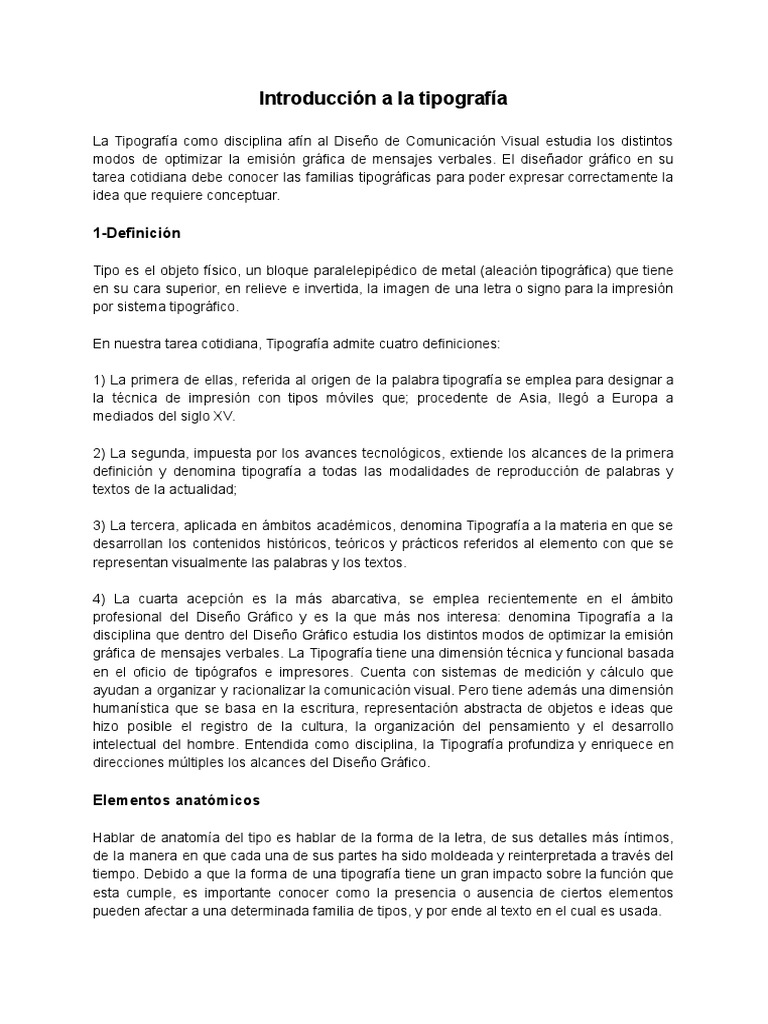
Introducción a la tipografía
La Tipografía como disciplina afín al Diseño de Comunicación Visual estudia los distintos
modos de optimizar la emisión gráfica de mensajes verbales. El diseñador gráfico en su
tarea cotidiana debe conocer las familias tipográficas para poder expresar correctamente la
idea que requiere conceptuar.
1-Definición
Tipo es el objeto físico, un bloque paralelepipédico de metal (aleación tipográfica) que tiene
en su cara superior, en relieve e invertida, la imagen de una letra o signo para la impresión
por sistema tipográfico.
En nuestra tarea cotidiana, Tipografía admite cuatro definiciones:
1) La primera de ellas, referida al origen de la palabra tipografía se emplea para designar a
la técnica de impresión con tipos móviles que; procedente de Asia, llegó a Europa a
mediados del siglo XV.
2) La segunda, impuesta por los avances tecnológicos, extiende los alcances de la primera
definición y denomina tipografía a todas las modalidades de reproducción de palabras y
textos de la actualidad;
3) La tercera, aplicada en ámbitos académicos, denomina Tipografía a la materia en que se
desarrollan los contenidos históricos, teóricos y prácticos referidos al elemento con que se
representan visualmente las palabras y los textos.
4) La cuarta acepción es la más abarcativa, se emplea recientemente en el ámbito
profesional del Diseño Gráfico y es la que más nos interesa: denomina Tipografía a la
disciplina que dentro del Diseño Gráfico estudia los distintos modos de optimizar la emisión
gráfica de mensajes verbales. La Tipografía tiene una dimensión técnica y funcional basada
en el oficio de tipógrafos e impresores. Cuenta con sistemas de medición y cálculo que
ayudan a organizar y racionalizar la comunicación visual. Pero tiene además una dimensión
humanística que se basa en la escritura, representación abstracta de objetos e ideas que
hizo posible el registro de la cultura, la organización del pensamiento y el desarrollo
intelectual del hombre. Entendida como disciplina, la Tipografía profundiza y enriquece en
direcciones múltiples los alcances del Diseño Gráfico.
Elementos anatómicos
Hablar de anatomía del tipo es hablar de la forma de la letra, de sus detalles más íntimos,
de la manera en que cada una de sus partes ha sido moldeada y reinterpretada a través del
tiempo. Debido a que la forma de una tipografía tiene un gran impacto sobre la función que
esta cumple, es importante conocer como la presencia o ausencia de ciertos elementos
pueden afectar a una determinada familia de tipos, y por ende al texto en el cual es usada.
Desde sus orígenes los caracteres han sufrido una constante transformación, de lo antiguo
a lo moderno, de lo sobrio a lo exagerado, de lo orgánico a lo sintético. Durante este
proceso han recibido infinidad de aportaciones, muchas veces dependiendo del contexto
histórico, político, económico y social del que formaban parte. Es gracias a estas
características que podemos clasificar las tipografías, aun cuando surgen ciertos conflictos
para llevar a cabo dicha tarea
Clasificación
Familias tipográficas
Una familia tipográfica es un grupo de tipografías unidas por características similares. Los
miembros de una familia (los tipos) se parecen entre sí, pero también tienen rasgos propios.
Las tipografías de cada familia tienen distintos grosores y anchos. Algunas familias las
forman muchos miembros, otras sólo de unos pocos.
Fuentes tipográficas
La palabra fuente se utiliza actualmente para describir todos los elementos anteriores más
las cursivas, finas y negras de la misma familia de tipos. Una tipografía está compuesta por
los conjuntos de caracteres representados por todos los tamaños y grosores de una
determinada clase de letra.
Resumen
El tipo básicamente es un caracter de impresión, una tipografía está compuesta por los
conjuntos de caracteres representados por todos los tamaños y grosores de una
determinada clase de letra los cuales son indispensables en el diseño gráfico. Los tipos se
pueden clasificar en fuentes, familias y series, para lograr estas clasificaciones nos vamos a
aprovechar de sus rasgos característicos y estilos.
Conclusión
La clasificación de los tipos y sus características nos va ayudar a identificarlos y poder
expresar la idea o mensaje que queramos o necesitemos.
2- Estructura
El vocabulario usado para la descripción de las diferentes partes que estructuran una letra,
se compone de una serie de términos acuñados desde hace mucho tiempo y que se
asemejan a los usados para describir las partes de nuestro cuerpo. Así las letras tienen
brazos, piernas, ojos, y otras partes como cola.
De cualquier forma, por problemas de traducción, la descripción de las partes de una letra
no coinciden de forma unánime en los libros sobre tipografía y diseño. En todo caso los
términos que aquí se reflejan constituyen un buen bagaje para comprender y conocer las
distintas partes de una letra.
Clasificación tipográfica
En la actualidad el universo de las tipografías resulta extremadamente amplio, más teniendo
en cuenta que gracias al desarrollo de las herramientas de informática y computación el
número se acrecienta en forma constante y a un ritmo sorprendente. Resulta prácticamente
imposible conocer por sus nombres la totalidad de las fuentes tipográficas, por lo que
intentar realizar una clasificación tipográfica comienza a tener sentido.
Una clasificación puede ser abordada desde ópticas diferentes:
● Una forma muy amplia de dividir el inmenso universo tipográfico puede ser teniendo
en cuenta la función o el empleo que se haga de la tipografía. Los dos grandes
grupos que se pueden reconocer con cierta facilidad en este sentido son: por un
lado, los de las tipografías que sirven para textos de largo alcance, es decir
tipografías que deben leerse con facilidad, y en cuanto a su morfología, no deben
llamar la atención. Y por otro lado estarían las tipografías de rótulo. Estas son
tipografías que deben llamar la atención por sobre todo, y por supuesto deben poder
leerse, aunque no son recomendables para textos largos.
● Otra clasificación elemental está basada en características relacionadas con la
anatomía de la letra, y si bien toma como referente la clasificación realizada por
Maximilian Vox en 1954, apunta a lograr una simplificación respecto a los estilos
transicionales. La clasificación aquí propuesta reconoce cuatro amplios grupos o
conjuntos básicos:
○ Tipografías Serif (Con Serif o Roman),
○ Tipografías Lineales (Sin Serif o Paloseco),
○ Tipografías Cursivas (o Script) y
○ Tipografías Decorativas (o Graphic)
Cada conjunto está subdividido en estilos, de los cuales a continuación daré algunas
características básicas y ejemplos de fuentes digitalizadas.
Sin desmedro de la clasificación propuesta, existen en la actualidad familias tipográficas
seriales o superfamilias que superan todas las barreras de los grupos clasificatorios, como
por ejemplo la tipografía Rotis, diseñada por Olt Aicher, que presenta un programa
tipográfico de cuatro alternativas de estilo: Sans Serif, Semi Sans, Semi Serif y Serif.
Tipografías con Serif (Con Serif o Roman)
Romanas Antiguas y Romanas Modernas: son tipografías que poseen serif y presentan
diferencias en los trazos. Derivan de las inscripciones romanas. En general son tipografías
con buena legibilidad y se utilizan habitualmente para textos de largo alcance. (Ejemplos:
Garamond / Times / Bembo) (Ejemplos: Bodoni / Modern / Didot)
Las tipografías egipcias se distinguen principalmente por el serif cuadrangular. Pueden
presentar o no diferencia en los trazos. En general son más pesadas que las romanas, y
son utilizadas frecuentemente para títulos o rótulos. No es aconsejable su uso para textos
largos. (Ejemplos: Clarendon / Serifa / Schadow)
Tipografías Lineales (Sin Serif o Paloseco)
Estas tipografías no presentan ningún tipo de serif o remate ni diferencia en los trazos. Se
caracterizan por una construcción rígida, donde predominan las formas geométricas en
apariencia puras.
Las tipografías cursivas
Las “cursivas” se utilizan para designar a las tipografías cuya apariencia se asemeja o está
inspirada en la tipografía hecha a mano. Las tipografías cursivas exhiben una fluidez y una
gracia sensible propia del gesto manual, y una morfología relacionada con el elemento
escriptor.
Tipografías Decorativas (Graphic)
En el conjunto de tipografías decorativas, fantasía o graphics, entrarían todos los tipos de
letra cuyas características no se ajustan a las de los conjuntos anteriores. Son tipografías
que en su mayoría han sido creadas con fines específicos, y donde el aspecto de legibilidad
no se ha tenido demasiado en cuenta. A menudo presentan una gran carga expresiva, a
través de atributos temáticos. Definitivamente, no son tipografías adecuadas para bloques
de textos.